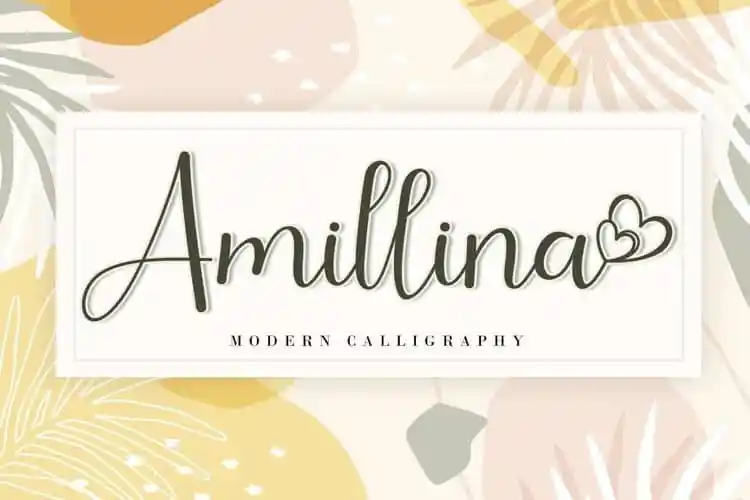
Descubra a elegância única da Amillina Calligraphy Font, uma tipografia escrita à mão que transmite classismo através do cálculo moderno e fresco. Esta fonte possui caracteres bem equilibrados e delicadamente desenhados, garantindo harmonia em um vasto range de design. Perfeita para quem busca inspiração e criatividade em seu trabalho, a Amillina Calligraphy Font irá transformar suas ideias mais audaciosas. Suportada por PUA encoding, você pode facilmente acessar todos os caracteres e desenhos ornamentais dessa fonte incrível. Adicionar esta tipografia ao seu arsenal de design certamente o tornará ainda mais único e inovador. Seja um designer ou criador de conteúdo, a Amillina Calligraphy Font está aqui para revolucionar suas criações.